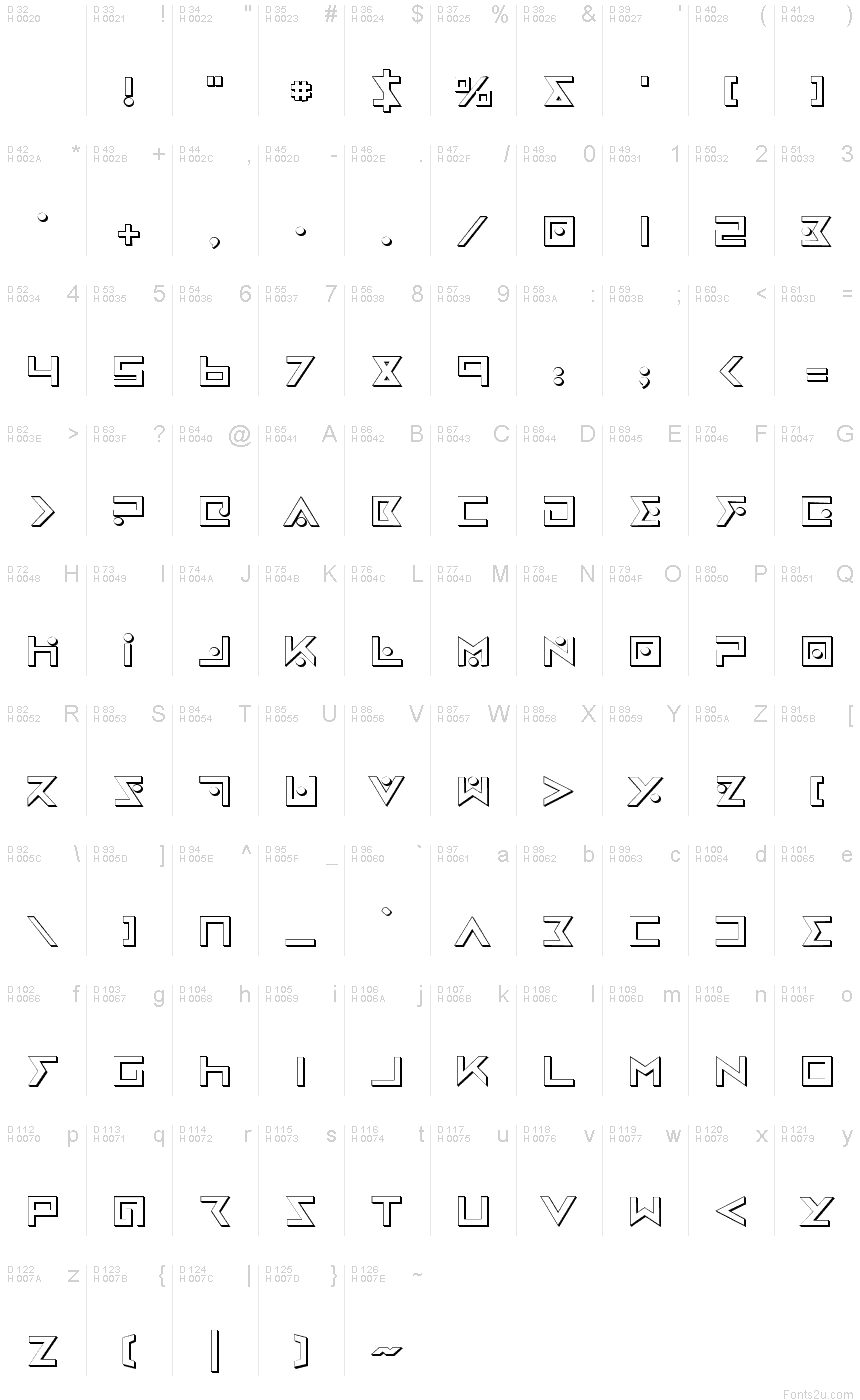
Iron Cobra 3D od Iconian Fonts to bezpłatny techniczny font 3D display z klimatem ery arcade. Litery zbudowane są z ostrych kątów, kanciastych załamań i otwartych cieni wewnętrznych, dzięki czemu formy sprawiają wrażenie wyciętych z metalu lub złożonych ze światła, z odpowiednią dawką nieregularności, która ożywia geometrię.
Naturalnie pasuje do logotypów gier, plakatów sci-fi, banerów na YouTube, okładek albumów i plansz tytułowych – wszędzie tam, gdzie darmowy font potrzebuje ruchu, nie wpadając w styl grunge. Zarysowana głębia sprawia, że nagłówki i krótkie bloki tekstu są dynamiczne, a krój świetnie sprawdza się w nazwach, monogramach i napisach na okładkach, którym zależy na energicznym, retro-futurystycznym sznycie.
Iron Cobra 3D